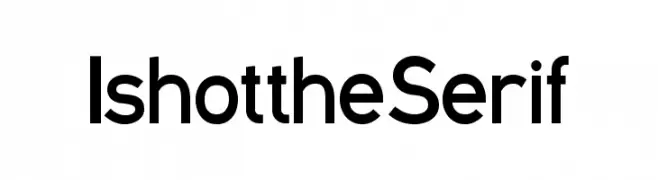
A grungy, distressed font with a splattered ink effect and irregular strokes.
A playful, sketch-like font with dynamic, irregular lines and a hand-drawn appearance.
A playful, bold font with irregular, hand-drawn letterforms.
A bold, decorative font with dot accents above each character.
A bold, condensed sans-serif font with clean lines and high legibility.
现在大家都在用哪些新字体?
流行变化很快,但极简无衬线与个性鲜明的展示体当前更受欢迎, 特别适合移动端内容与现代品牌风格。
有哪些值得尝试的 5 款新字体?
近期热门包括 IshottheSerif, Shoes center, Vtks Grungy, TwinkleFingers and DHF A Great Happiness 它们在清晰度与个性之间取得平衡,适用于科技品牌、编辑排版与社媒视觉。